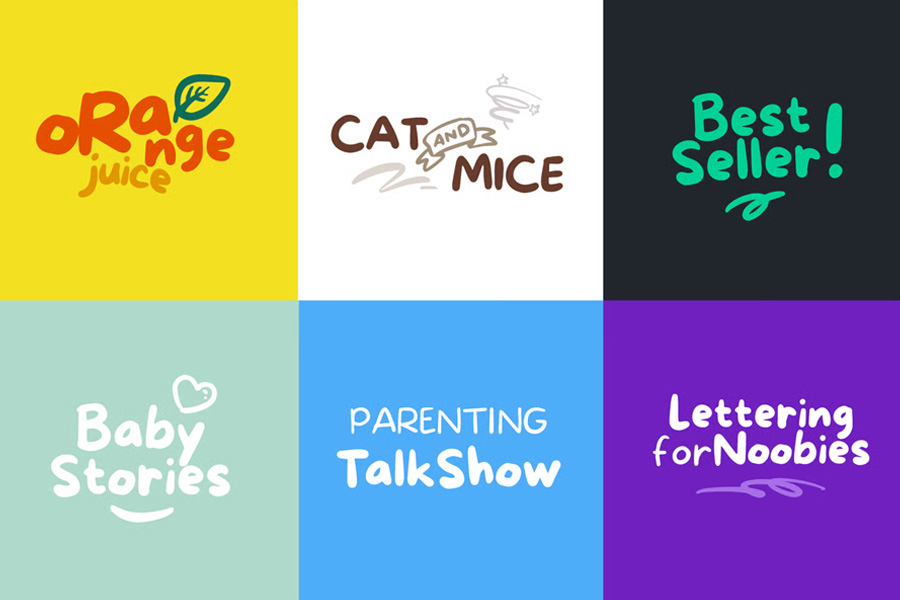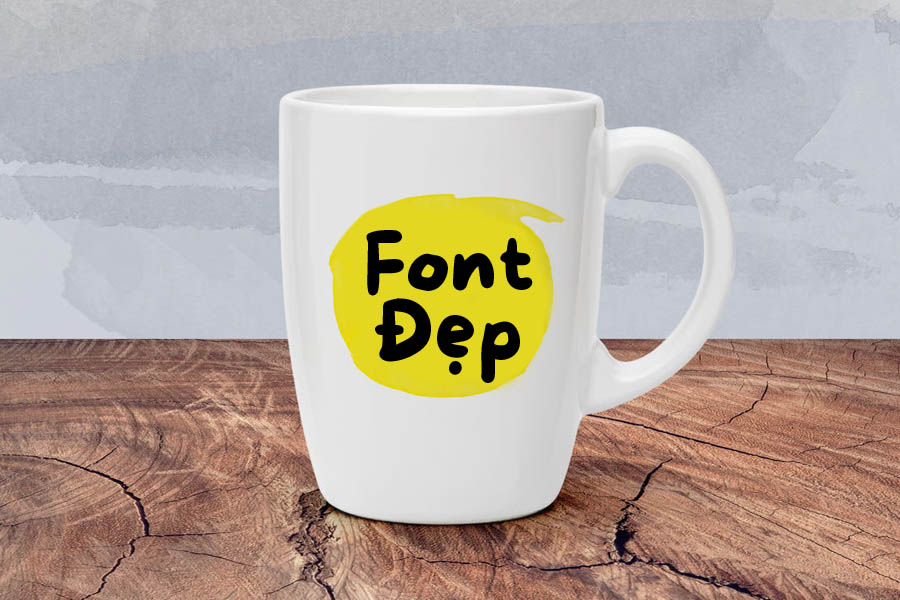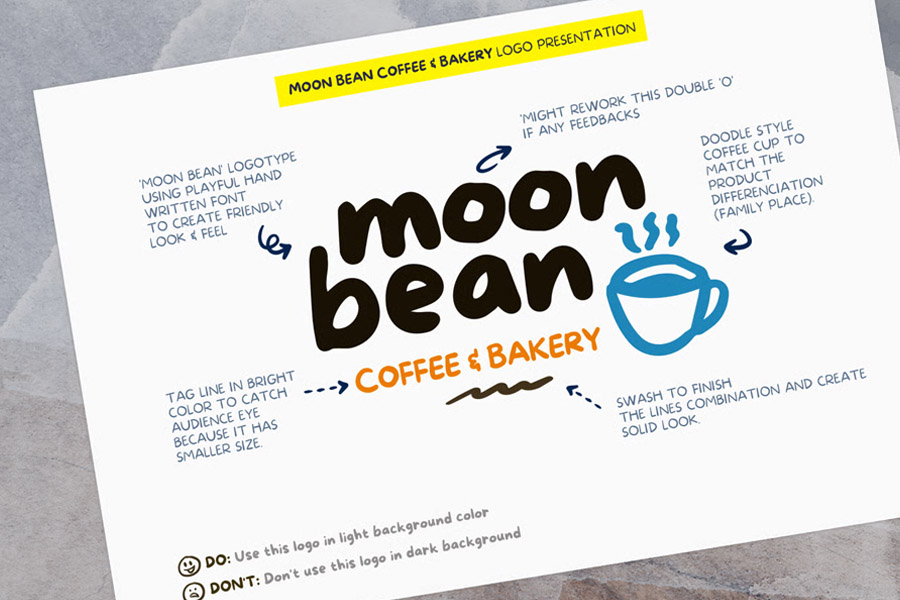
Font chữ Hoạt Hình Vui Nhộn TH More Sugar Việt Hóa
Font chữ TH More Sugar là một trong những lựa chọn tuyệt vời cho những ai yêu thích phong cách thiết kế đáng yêu và nổi bật. Đúng như tên gọi, TH More Sugar mang đến cảm giác ngọt ngào như những viên kẹo, với các nét chữ tròn trịa, béo đầy và bo góc mềm mại. Đây là kiểu font chữ display được nhiều nhà thiết kế lựa chọn để tạo điểm nhấn trong các dự án sáng tạo, từ bao bì sản phẩm đến poster sự kiện.
Điểm nổi bật của T More Sugar nằm ở sự cân đối và dễ đọc, ngay cả khi hiển thị ở kích thước nhỏ. Font sở hữu những đường nét dày dặn, căng đầy, mang lại hiệu ứng thị giác mạnh mẽ nhưng vẫn giữ được sự thân thiện, gần gũi. Chính vì vậy, nó đặc biệt phù hợp với các thiết kế dành cho trẻ em, các thương hiệu đồ ăn vặt, bánh kẹo, nước giải khát hay các chiến dịch truyền thông cần yếu tố vui nhộn, trẻ trung.
Một tin vui cho cộng đồng thiết kế tại Việt Nam là font TH More Sugar đã được Phạm Sơn Việt hóa, giúp font hỗ trợ đầy đủ dấu tiếng Việt. Nhờ đó, bạn có thể dễ dàng áp dụng font này trong các dự án thiết kế phục vụ thị trường trong nước mà không gặp trở ngại về ngôn ngữ. Phiên bản Việt hóa vẫn giữ nguyên sự mềm mại, đáng yêu của bản gốc nhưng đồng thời đảm bảo tính tiện dụng và thân thiện cho người dùng Việt.
Không chỉ dừng lại ở khía cạnh thẩm mỹ, TH More Sugar còn mang đến sự linh hoạt trong ứng dụng. Bạn có thể sử dụng font này cho tiêu đề, logo, banner, thiệp chúc mừng hay các sản phẩm in ấn như áo thun và túi vải. Mỗi chữ cái đều gợi lên cảm giác năng động, tràn đầy sức sống, giúp thiết kế của bạn dễ dàng ghi điểm trong mắt người xem.
Với phong cách đáng yêu, tròn đầy và ngọt ngào, cùng phiên bản Việt hóa chuẩn bởi Phạm Sơn, TH More Sugar chắc chắn sẽ trở thành lựa chọn hàng đầu cho các nhà thiết kế khi muốn mang đến một diện mạo tươi mới, độc đáo và thu hút cho tác phẩm của mình.